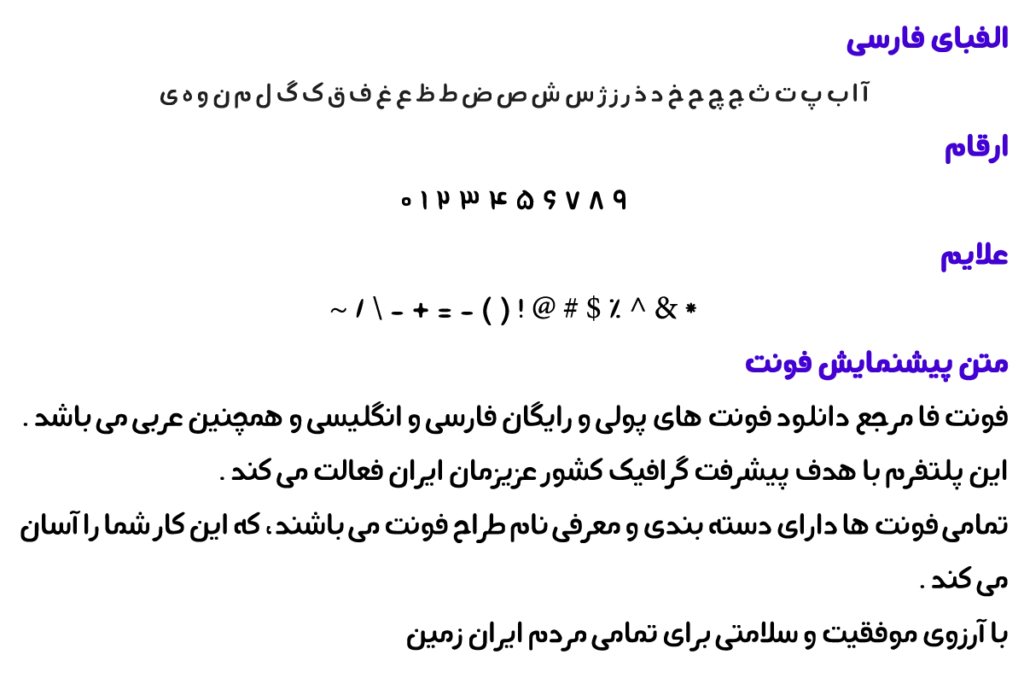
فونت فارسی نگار – A Negaar
طراح فونت: مجتبی کیا نوع فونت: فونت گرافیکی
توضیحات و معرفی فونت نگار
فونت فارسی نگار ( A Negaar ) از مجموعه فونت های آزاد می باشد، و نیز نوع فونت گرافیکی می باشد.
فونت خوشگل مربوط توسط مجتبی کیا طراحی و ساخته شده است.
و نیز فونت در 2 وزن پر رنگ و معمولی است.
- A Negaar Bold
- A Negaar Regular
در عکس زیر میتوانید این فونت زیبا را ببینید که باهاش شعر زیبای وطنم را طراحی کرده ایم.